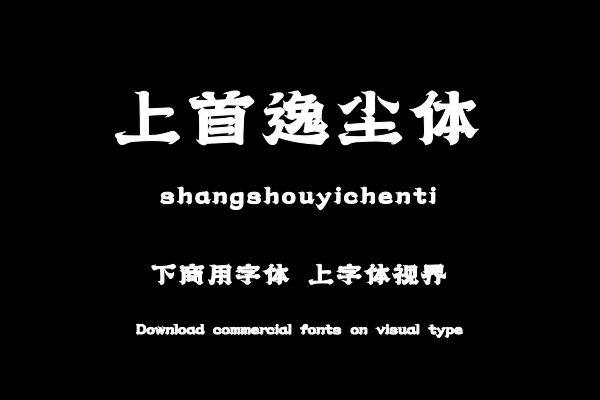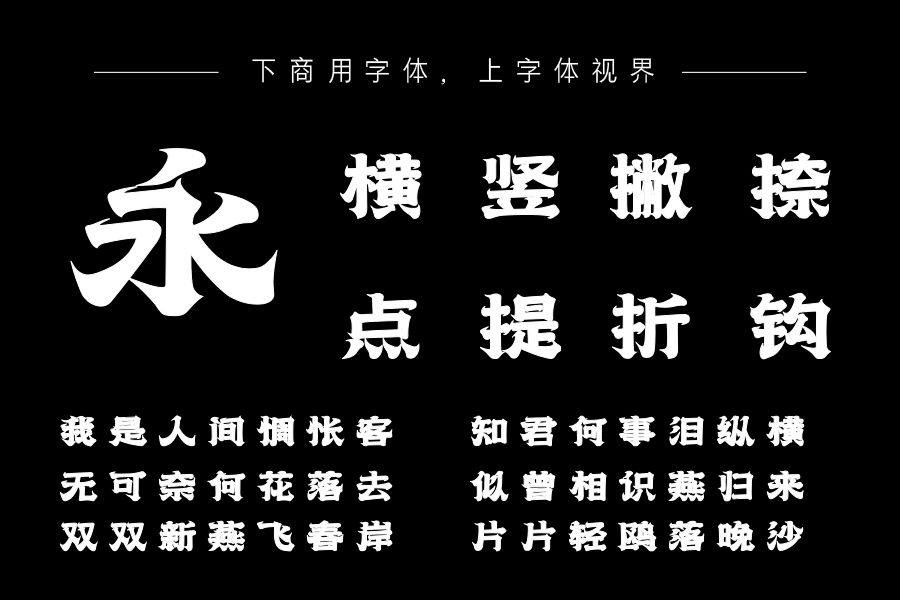
字体整体稳重大气,疏密得体。笔画粗细均衡,字形整体结构方正,但在笔画上结合了书法字体的一些笔画特征,使得字体在端庄稳重之余又不失大气洒脱。字体整体黑白均匀,符合......购买须知:“下载服务费”与“字体VIP”所获得字体 仅用于个人非商用, 商用请联系付费授权。本字体为电脑用字,手机没有root权限不支持直接手机换字(手机如何root,请自行百度搜索教程)。购买前请先 了解清楚后再付款 ,字体为虚拟产品无法回收 一旦购买不支持退款。